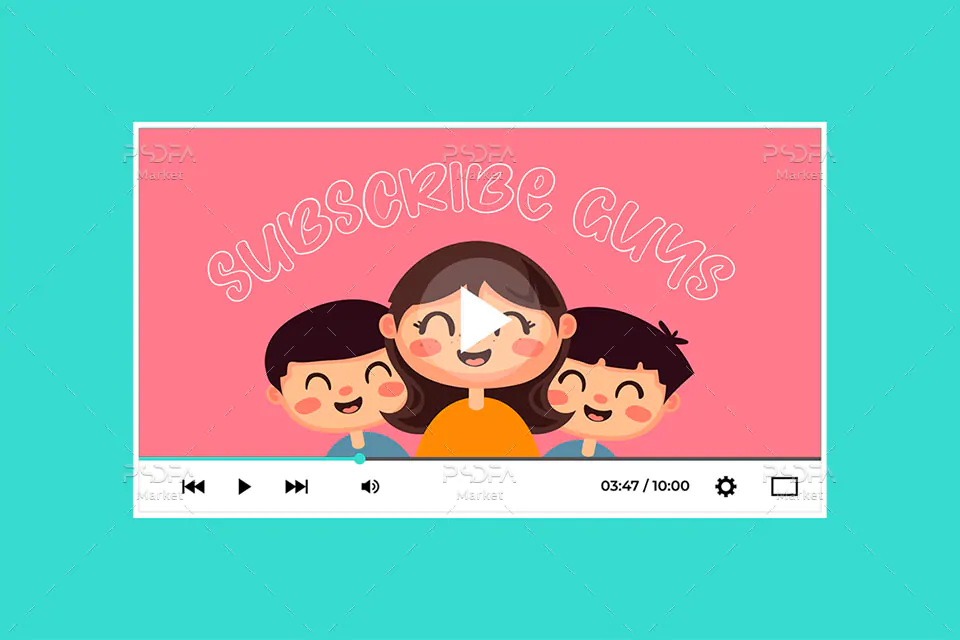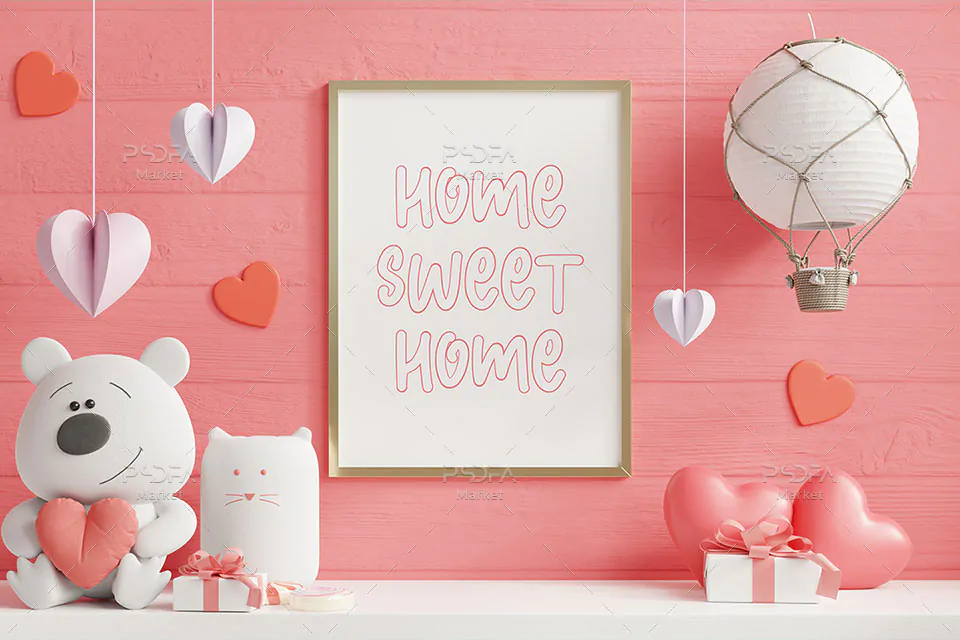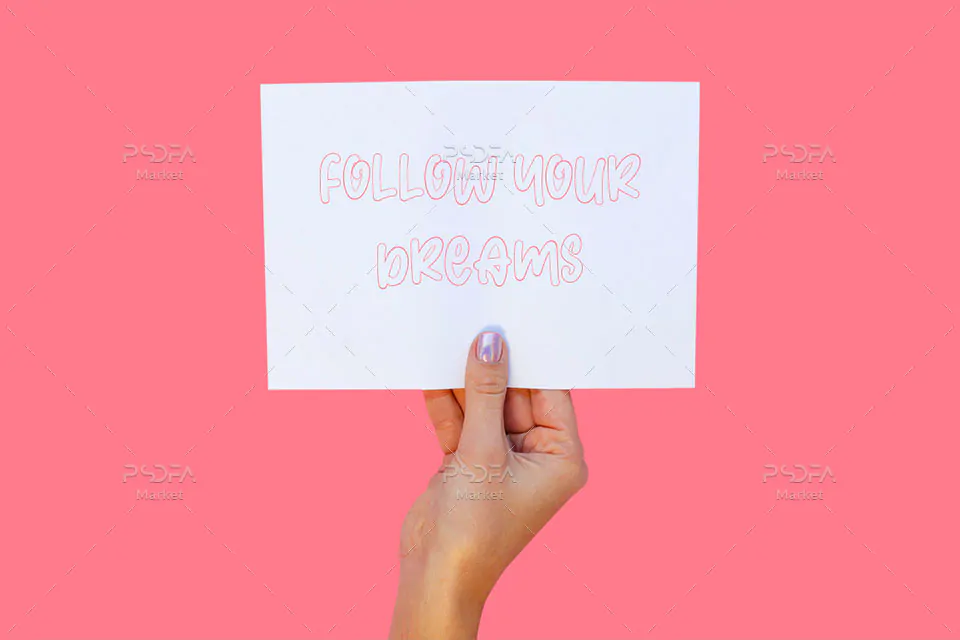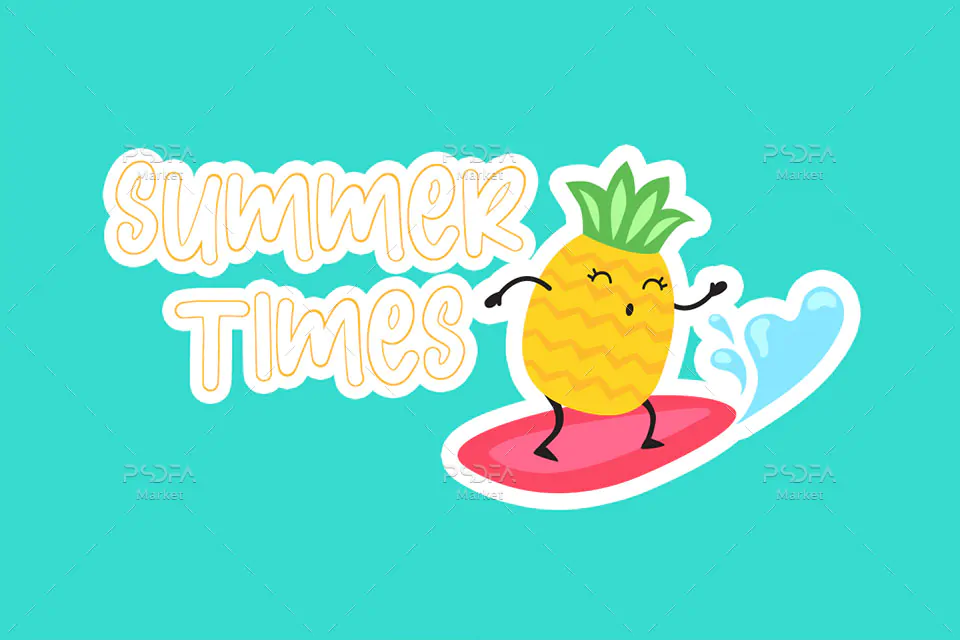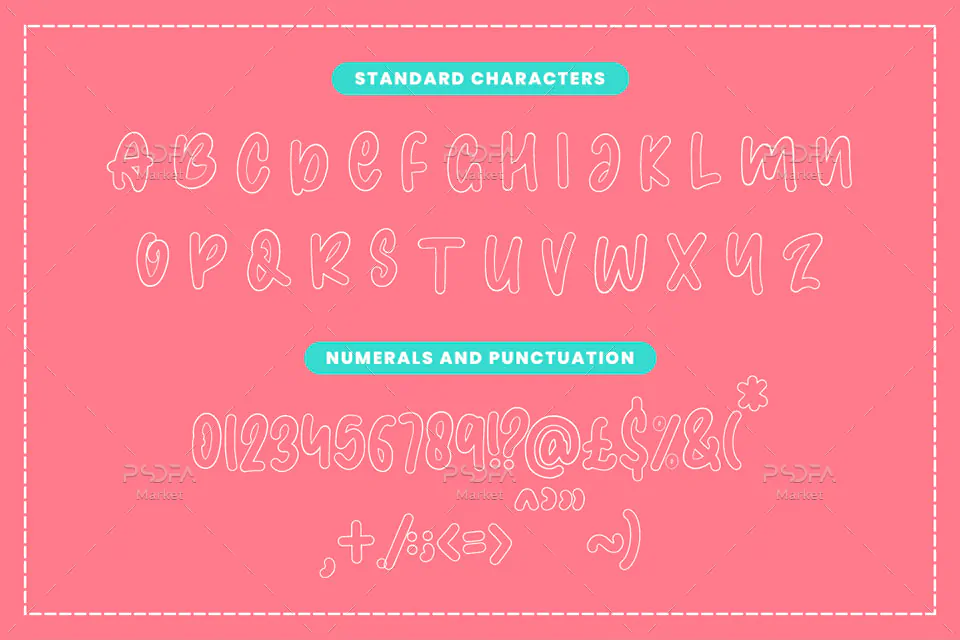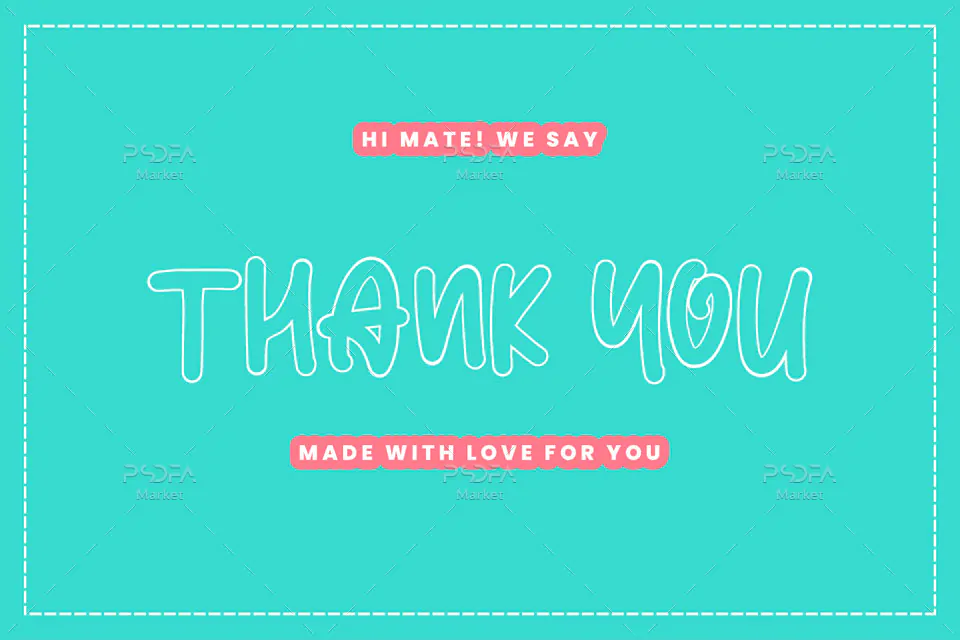
فونت توخالی کودکانه Funline
فونت توخالی کودکانه Funline یک قلم انگلیسی فانتزی است که مناسب جهت استفاده در طرح و پروژه‌های گرافیکی مختلف می‌باشد. این فونت در قالب فرمت‌های ttf, otf در فایل محصول قرار دارد که می‌توانید از آن در نرم افزارهای گرافیکی مختلف استفاده کنید.
فونت Funline با وزن معمولی طراحی شده است که می‌توان در طراحی انواع کارت تبریک، کارت پستال، تقویم، بنر، پوستر، پارچه و لباس، لیوان و ماگ، ظروف یکبار مصرف، لوازم التحریر، بسته بندی محصولات و … استفاده نمود.